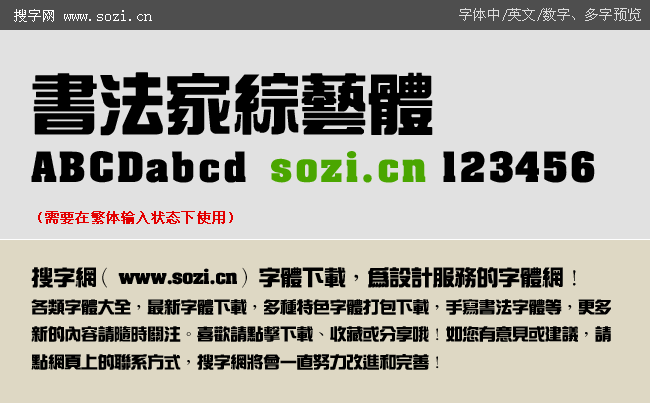
書法家綜藝體
搜字網(wǎng)提供一款書法家綜藝體下載。此款為繁體字體,綜藝體是黑體的一種變體,也是藝術(shù)字的一種。特點(diǎn)是筆劃更粗,盡量將空間充滿。同時(shí)為了美觀,對(duì)拐彎處的處理較為圓潤。適用于廣告、報(bào)刊等的標(biāo)題及海報(bào)展板等設(shè)計(jì)場(chǎng)合使用。